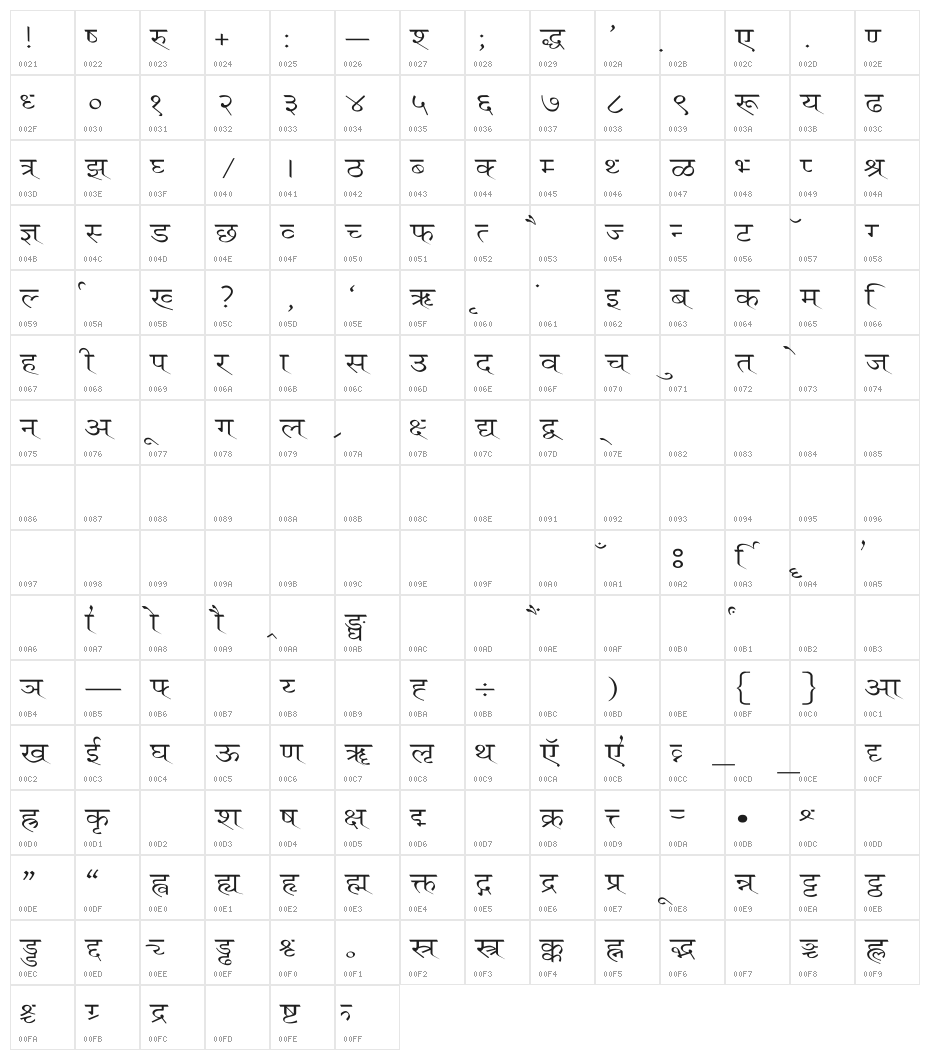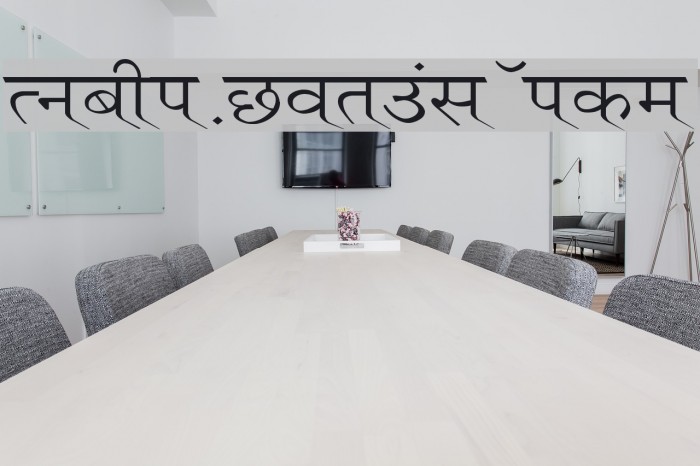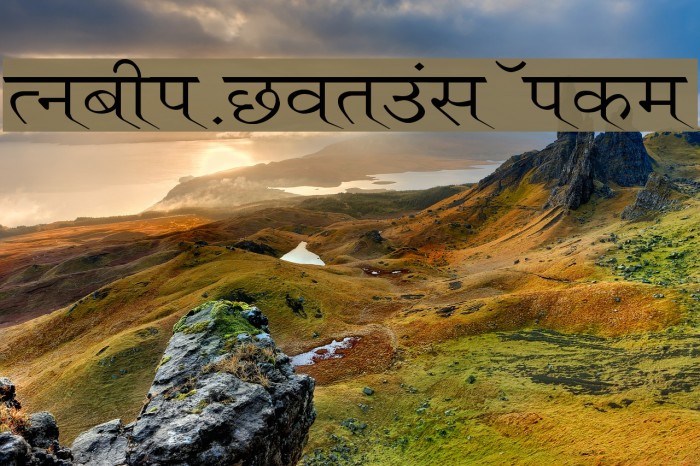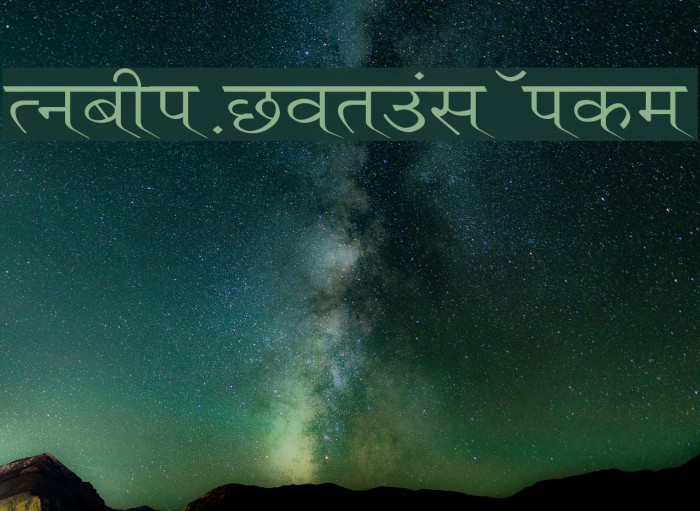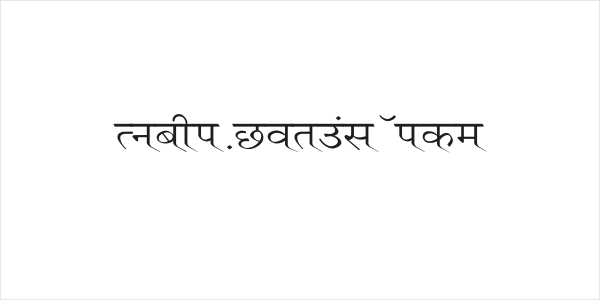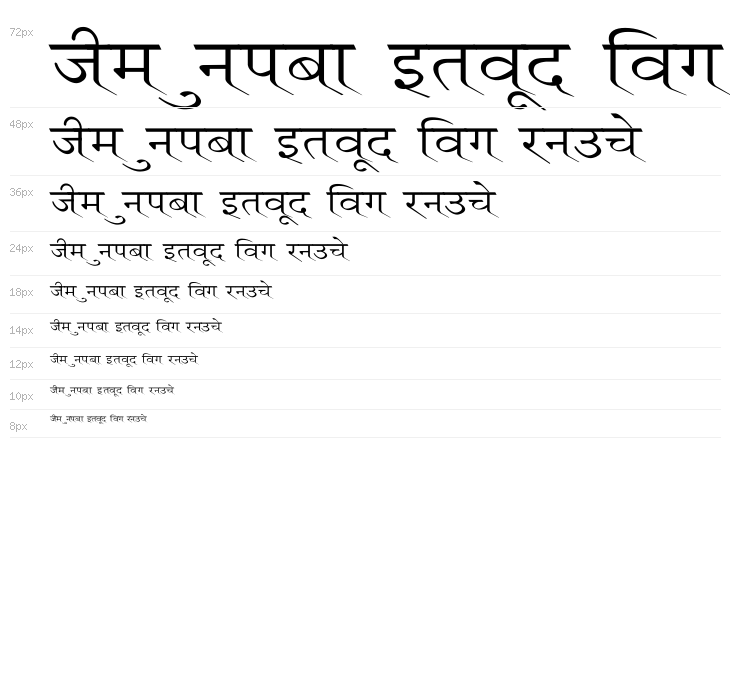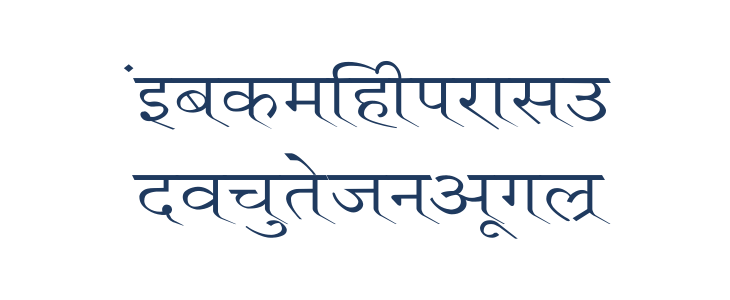
Ruchi-Normal Wide Font
| Caz de utilizare | Headlines, Logos, Signage |
| Proiecte propuse | Ideal for cultural publications, branding, signage, and digital media that require a traditional yet modern look. |
Ruchi-Normal Wide